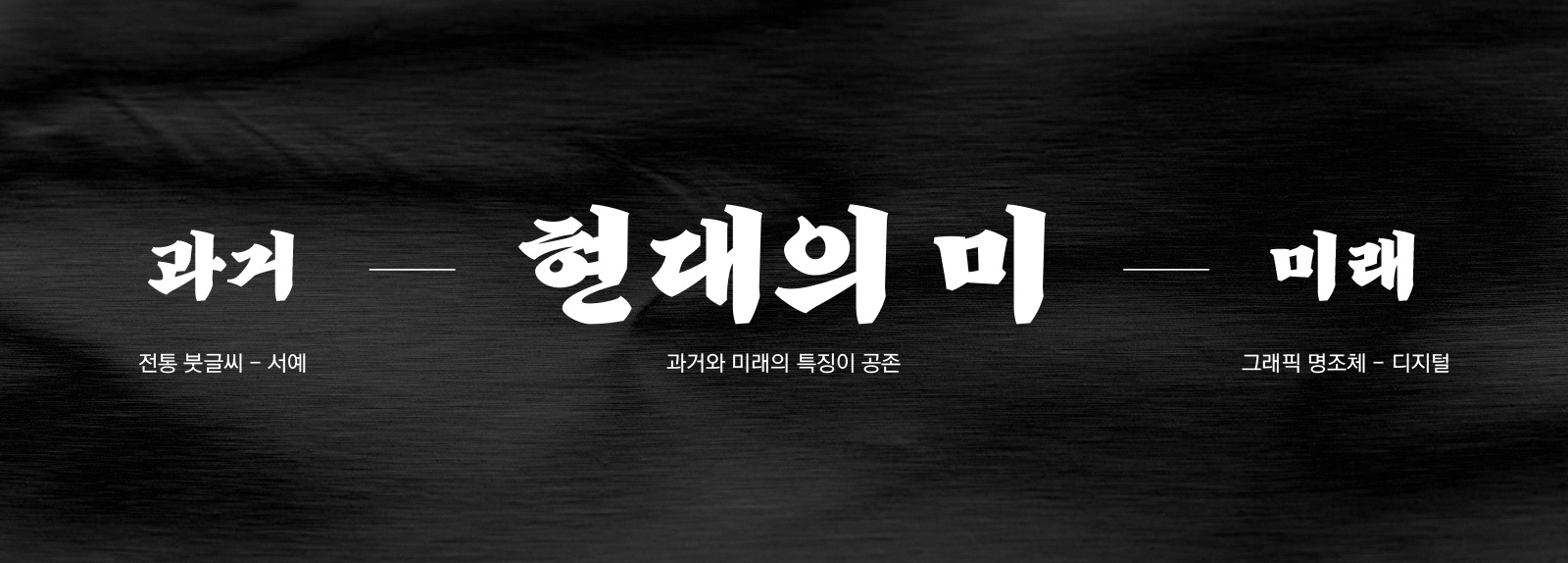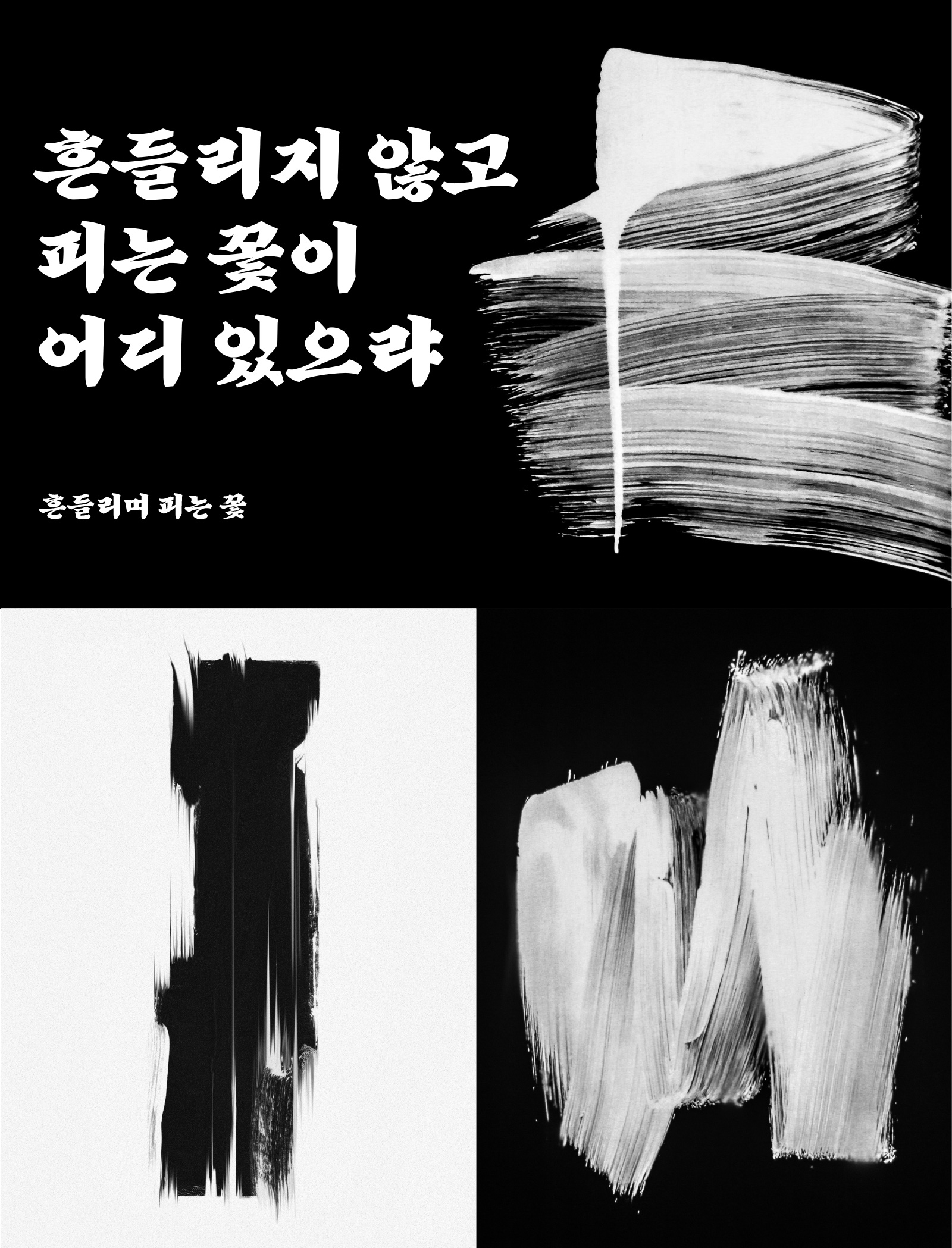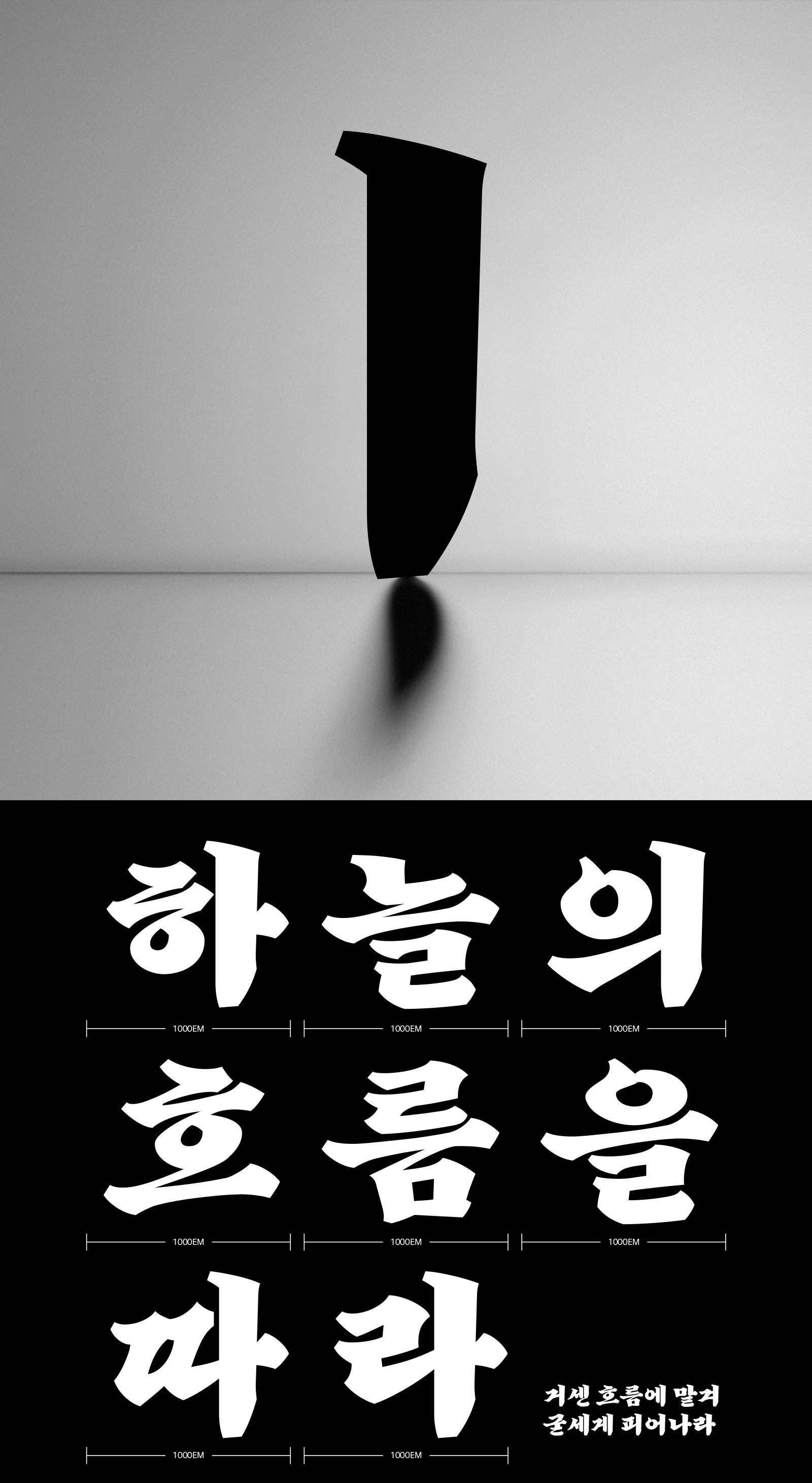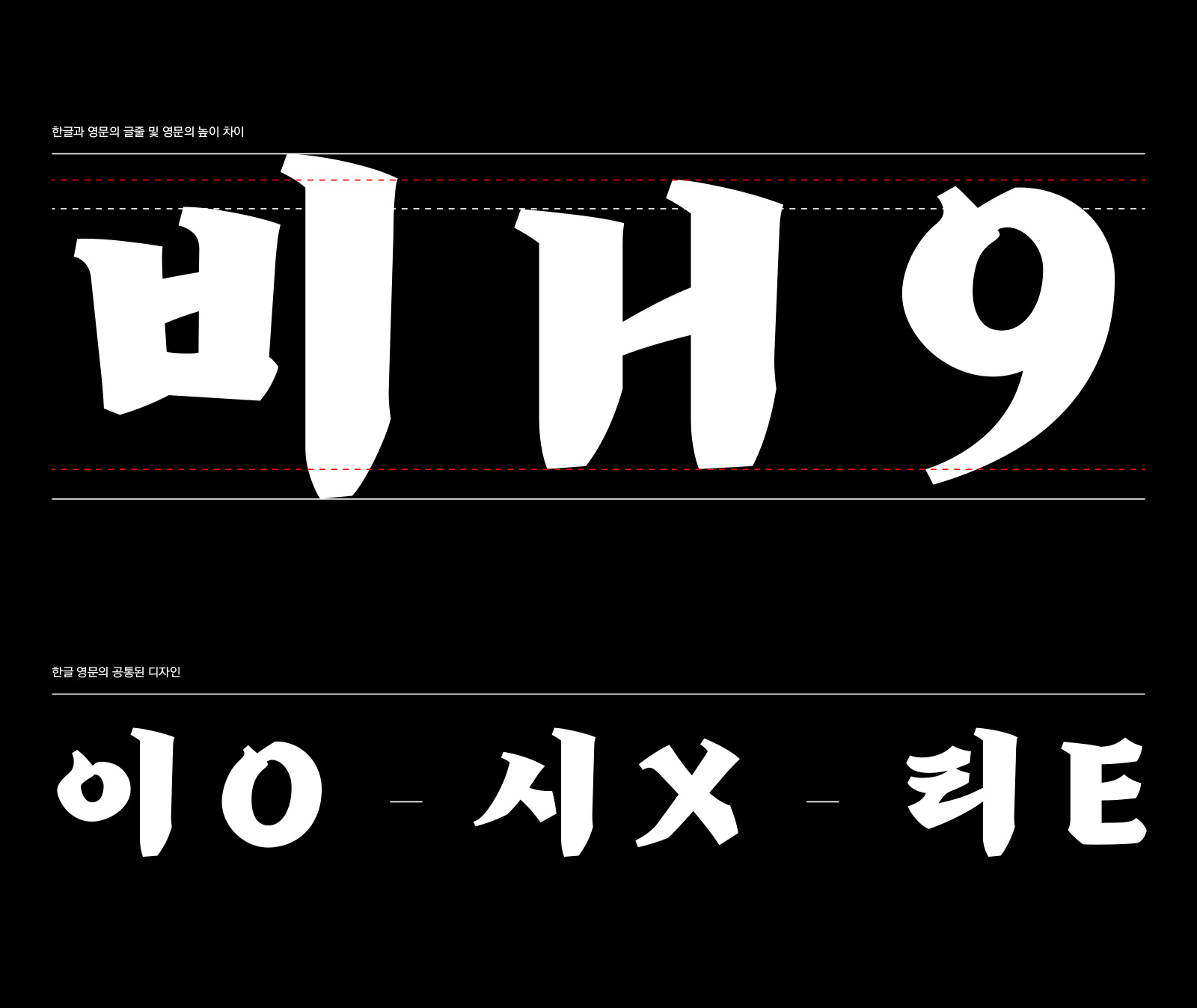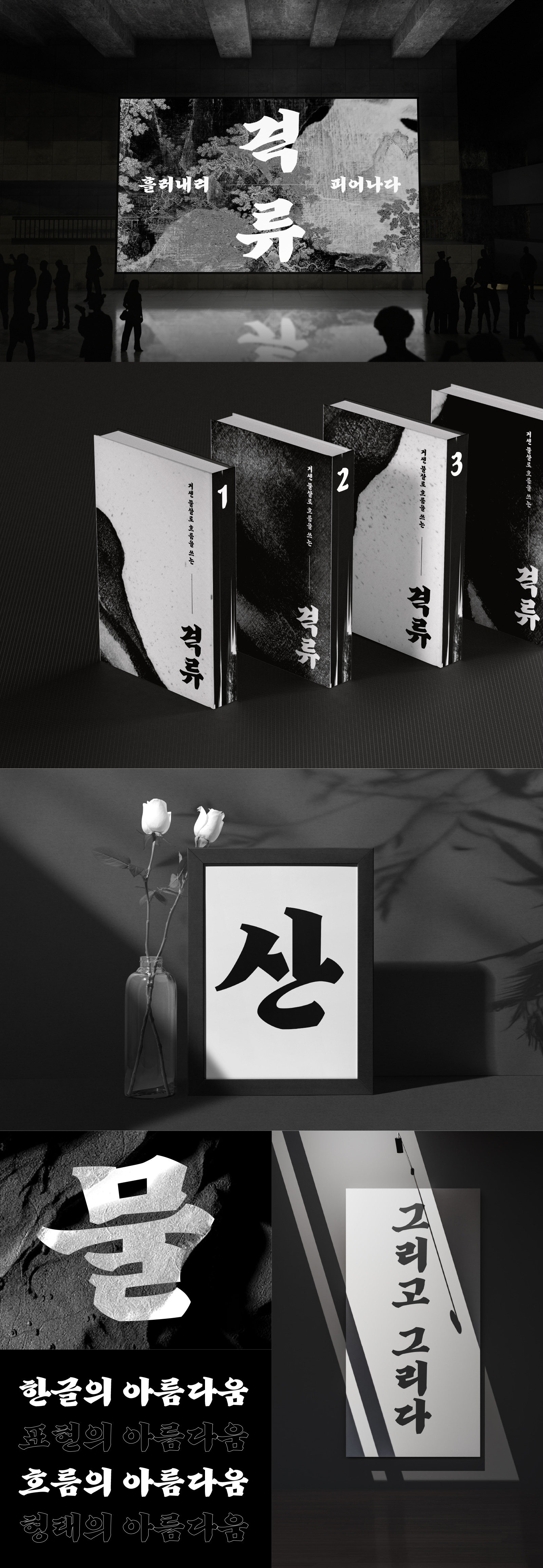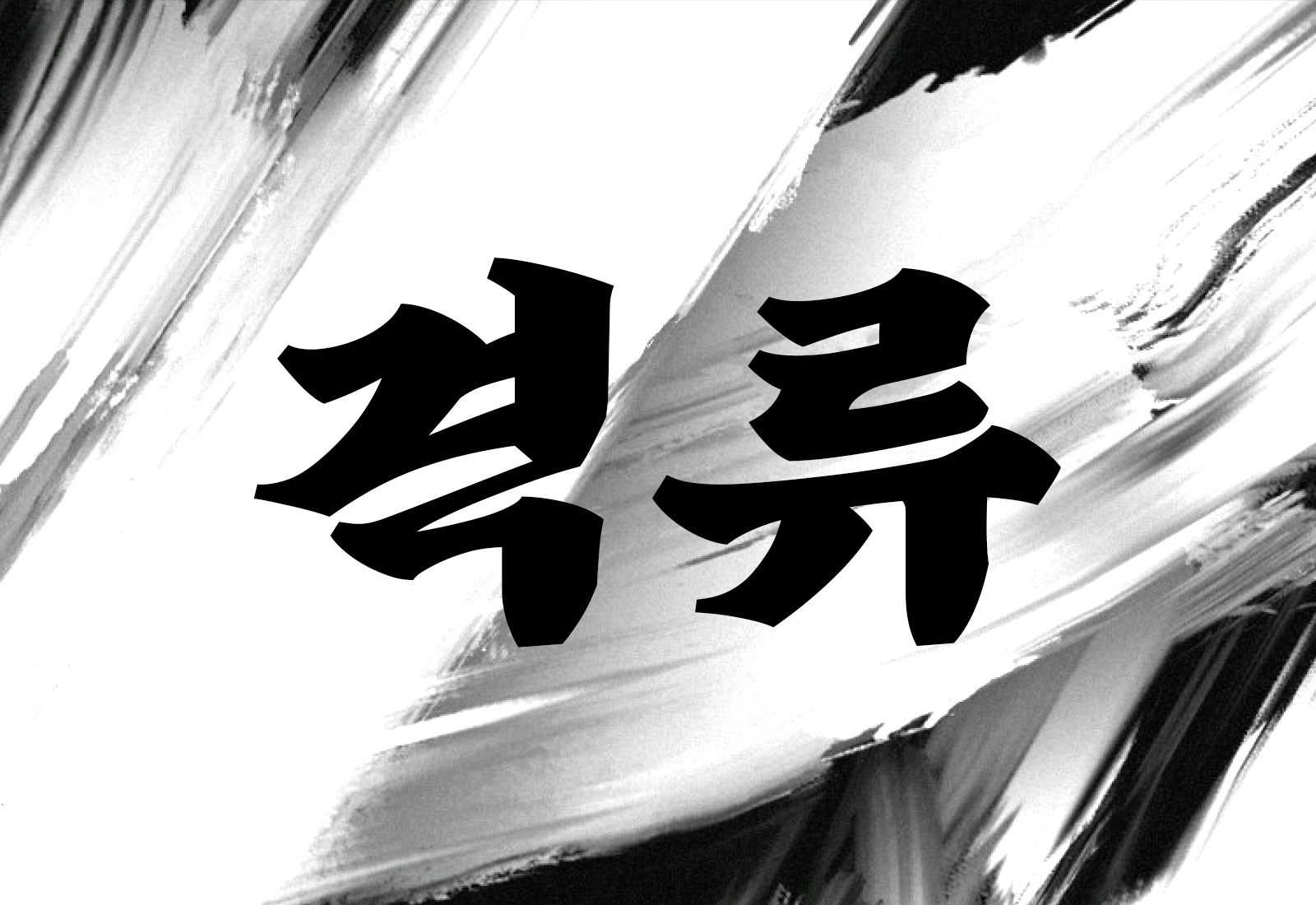
RixRiptide
1 Style - RegularRix격류는 강한 획의 흐름으로 붓글씨의 특성을 반영한 서체입니다.
기존 붓글씨 서체의 올드한 이미지를 없애고 세련된 형태로 맺음을 가지며,
힘있는 인상으로 강한 메시지를 전달합니다.
| FontFamily | Rix격류 / RixRiptide |
|---|---|
| Design | Kim Jung-jin |
| Direction | Park Yong-rak |